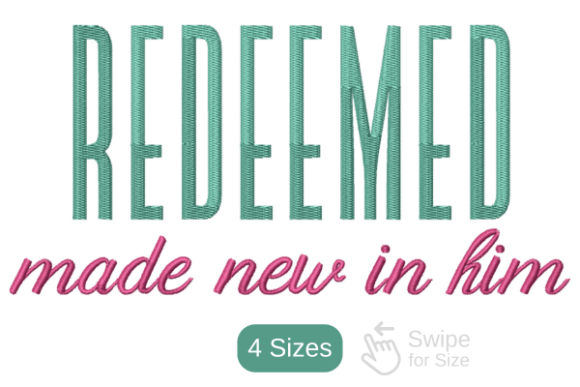
Redeemed in Him Embroidery
Trouver les bons éléments de conception peut être un défi, mais Redeemed in Him Embroidery propose une collection exceptionnelle qui rehausse instantanément votre travail.
Conçu avec précision, Redeemed in Him Embroidery offre des vecteurs nets, une typographie fluide et une licence commerciale pour une tranquillité d'esprit.
Que vous créiez des produits POD (impression à la demande), des invitations de mariage ou des visuels pour les réseaux sociaux, Redeemed in Him Embroidery est un choix idéal.